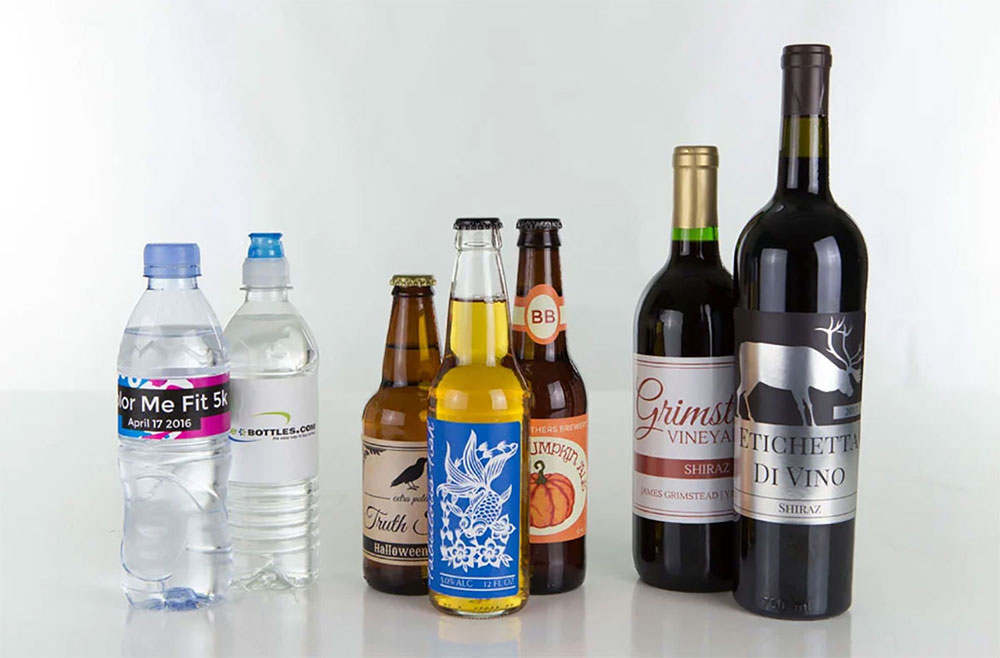
Die Auswahl der besten Schriftarten für Etiketten ist wie das Aussuchen des perfekten Outfits für ein großes Ereignis. Es kann alles verändern.
Stellen Sie sich vor, Sie betreten einen Laden, Ihre Blicke schweifen über die Regale, und da ist es – ein Produkt, das heraussticht, nicht nur wegen seines Inhalts, sondern wegen seiner Präsentation. Das ist die Macht der Schriftarten.
In diesem Tauchgang in die Welt der Typografie enthüllen wir die geheime Zutat, die Etiketten nicht nur lesbar, sondern unvergesslich macht.
Ob Sie ein Kleinunternehmer sind, der seine Produktverpackung aufpeppt, oder eine neugierige Seele, die vom Einfluss der Typografie im Marketing fasziniert ist, dies ist für Sie.
Wir sprechen über alles, von Serifen- und serifenlosen Schriftarten, die Professionalität ausstrahlen, bis hin zu ausgefallenen handschriftlichen Schriftarten, die diesen handwerklichen Vibe vermitteln.
Am Ende dieser Reise werden Sie mit Wissen über Schriftlesbarkeit, Designprinzipien und darüber ausgestattet sein, wie Schriftarten mit Ihrer Markenidentität übereinstimmen können.
Machen Sie sich bereit, eine Vielzahl von Typografietrends zu erkunden und wie sie Ihr Etikettenspiel verbessern können. Von gut lesbaren Schriftarten für die kleinen Etiketten bis hin zu fetten Schriftarten für einen auffälligen Look, wir haben alles abgedeckt.
Die besten Schriftarten für Etiketten
| Schriftartenname | Kategorie/Stil | Lesbarkeit | Verwendungszweck | Besondere Merkmale |
|---|---|---|---|---|
| Garamond | Serif | Hoch | Fließtext, anspruchsvolle Etiketten | Elegant, klassisches Design, gut für den Druck |
| Butler | Serif | Hoch | Stilvolle Etiketten, Überschriften | Moderne Interpretation der traditionellen Serifenschrift |
| Yeseva One | Serif | Mittel | Dekorative Etiketten, Schlagzeilen | Einzigartig, fett mit hohem Kontrast |
| Didot | Serif | Mittel | Etiketten für hochwertige Produkte, Mode | Stilvoll, gehoben mit dünnen Serifen |
| Times New Roman | Serif | Hoch | Allgemeine Nutzung, Fließtext | Klassisch, bekannt, weit verbreitet |
| Cambria | Serif | Hoch | Allgemeine Etiketten, gut lesbarer Druck | Optimierte Lesbarkeit auf Bildschirmen |
| Georgia | Serif | Hoch | Vielseitige Etiketten, Bildschirm und Druck | Hervorragende Lesbarkeit, elegant |
| Baskerville | Serif | Hoch | Traditionelle Etiketten, Buchtext | Gepflegtes, professionelles Design |
Arten von Schriftarten für Etiketten
Serifenschriftarten
Ah, Serifenschriftarten, die klassische Wahl! Denken Sie an sie wie an das zeitlose kleine Schwarze in Ihrem Kleiderschrank. Es sind nicht nur Schriftarten; sie sind eine Aussage von Eleganz und Vertrauenswürdigkeit. Warum? Weil diese Schriftarten jene kleinen Füße am Ende jedes Buchstabens haben, bekannt in der Designwelt als Serifen. Und raten Sie mal? Sie machen Ihre Etiketten super lesbar, besonders für längeren Text.
Einige Top-Picks? Garamond – er ist wie jener weise, alte Professor, der weiß, wie man komplizierte Dinge einfach aussehen lässt. Dann gibt es Butler – stellen Sie sich einen Butler vor, aber für Ihre Worte, der sie scharf und anspruchsvoll aussehen lässt. Yeseva One fügt eine Note von Wärme hinzu, ideal für jene gemütlichen, wohlfühlenden Produkte.
Didot ist Ihre Wahl für Luxusvibes auf hohem Niveau. Es ist, als würden Sie Ihrem Text einen Designanzug anziehen. Und wer könnte Times New Roman und Cambria vergessen? Sie sind wie Ihre zuverlässigen Freunde, die nie im Stich lassen, perfekt für jedes Etikett, das Zuverlässigkeit und Komfort kommunizieren möchte. Georgia und Baskerville fügen einen Hauch von altmodischem Charme hinzu, wodurch Ihre Etiketten sich anfühlen wie ein klassischer Roman.
Serifenlose Schriftarten
Wechseln wir die Gänge und sprechen über serifenlose Schriftarten. Serifenlos bedeutet „ohne Serifen“, und diese Schriftarten stehen für moderne, klare Linien. Sie sind wie das trendige, minimalistische Outfit, das Sie tragen, das modernen Schick ausstrahlt.
Erstens Aileron, schlicht und vielseitig. Es ist wie die Jeans, die zu allem passt. Maison Neue? Sie ist die anspruchsvolle Cousine, die einen Hauch von Eleganz mitbringt. Und Sofia – oh, sie ist spaßig und freundlich, perfekt für Etiketten, die zugänglich wirken wollen.
Omnes ist Ihre unbeschwerte Schriftart, während Helvetica und Arial die universellen Freunde in der Schriftartenwelt sind, bekannt und von allen geliebt. Für ein futuristisches Gefühl gibt es Futura – denken Sie daran als Ihre Sci-Fi-Fantasie in Schriftform. Calibri und Verdana sind Allrounder, großartig für nahezu jedes Etikett, während Roboto einen mechanischen und doch menschlichen Touch in den Mix bringt.
Schreibschriftarten
Okay, lassen Sie uns in die Welt der Schreibschriftarten eintauchen. Diese Schriftarten sind wie die Handschrift, die Sie sich wünschen, voller Flair und Persönlichkeit. Perfekt, wenn Sie möchten, dass Ihre Etiketten persönlich und handgefertigt wirken. Lucia Script? Es ist wie ein schön geschriebener Brief. Elegant, doch zugänglich. Satisfy? Genau wie sein Name hinterlässt es einen süßen, zufriedenstellenden Eindruck, ideal für Lebensmitteletiketten oder alles, was einen Hauch von Verspieltheit vermitteln möchte.
Jetzt, Bella Donna – diese hat eine ausgefallene Ausstrahlung, wie Kalligrafie, die Sie auf einer Hochzeitseinladung sehen würden. Homemade Apple bringt ein rustikales, heimeliges Gefühl auf den Tisch und erinnert an Omas Apfelkuchen. Und Loved by the King hat eine königliche Note, mit Schleifen und Wirbeln, die für eine Königin geeignet sind. Sue Ellen Francisco rundet es mit einem lässigen, luftigen Stil ab, wie eine schnelle Notiz, die von einem Freund gekritzelt wurde.
Display- und Dekorative Schriftarten
Weiter geht’s mit Display- und dekorativen Schriftarten – das sind die Hingucker. Sie sind wie das auffällige Schmuckstück, das Blicke auf sich zieht. Lemonade ist frisch und spaßig, perfekt für ein sommerliches Vibe. Shortcut Vintage Bundle Font nimmt Sie mit zurück in die Zeit mit seinem Retro-Charme, großartig für Marken, die eine nostalgische Note wollen.
Mermaid Typeface taucht tief in die Fantasie ein und gibt ein mystisches Gefühl unter Wasser. Gunnar ist stark und fett, und macht auf jedem Etikett eine Aussage. Buchin ist schrullig und unerwartet, für Marken, die es wagen, anders zu sein. Whimsy, wie der Name schon sagt, fügt eine verspielte, humorvolle Note hinzu.
Und dann gibt es Watch und Asthenia. Watch ist wie diese schlanke, moderne Uhr, die Sie tragen – es dreht sich alles um ein klares, wirkungsvolles Design. Asthenia, mit seinen dünnen, zarten Linien, ist perfekt für hochwertige, anspruchsvolle Produkte.
Handschriftliche und Pinselschriftarten
Zuletzt handschriftliche und Pinselschriftarten. Diese Schriftarten sind wie eine persönliche Signatur, jede mit ihrem eigenen Charakter und Stil. Habisa ist entspannt und unprätentiös, großartig für lässige oder handwerkliche Produkte. Crafty Girls bringt einen kreativen, künstlerischen Vibe, ideal für Bastelbedarf oder spaßige, jugendliche Marken.
Shadows into the Light und Waiting for the Sunrise sind leicht, luftig und optimistisch, perfekt für inspirierende oder Wellness-Produkte. Und Carbonera, mit seinen fett gedruckten Pinselstrichen, macht eine starke, selbstbewusste Aussage, großartig für Marken, die auffallen wollen.
Kriterien für Schriftlesbarkeit und -leserlichkeit
Wenn es darum geht, die besten Schriftarten für Etiketten auszuwählen, geht es nicht nur darum, hübsch auszusehen. Wir müssen darüber nachdenken, wie einfach es ist, diese Schriftarten zu lesen, besonders wenn jemand in Eile im Laden ist, wissen Sie?
Lesbarkeitsfaktoren
Erstens: Lesbarkeit. Es ist wie das Einrichten der richtigen Stimmungsbeleuchtung für ein Date. Wir sprechen über den Kontrast und die Sichtbarkeit der Schrift gegenüber dem Hintergrund des Etiketts. Zu viel oder zu wenig Kontrast, und Sie haben Ihr Publikum verloren.
Dann gibt es den Abstand zwischen den Buchstaben. Haben Sie schon einmal versucht, etwas zu lesen, bei dem die Buchstaben zusammengequetscht sind? Nicht lustig, oder? Der richtige Abstand, auch Kerning genannt, macht einen großen Unterschied.
Schließlich hat jede Schriftart ihren eigenen Stil, aber wir benötigen deutliche Buchstabenformen. Sie wollen nicht, dass das ‚b‘ wie ein ‚d‘ aussieht und allerlei Verwirrung stiftet.
Dyslexie-freundliche Schriftarten
Jetzt sprechen wir über etwas sehr Wichtiges: dyslexie-freundliche Schriftarten. Es geht um Inklusion. Diese Schriftarten sind so konzipiert, dass sie einfacher zu lesen sind, besonders für Menschen mit Dyslexie. Sie haben in der Regel schwerere untere Teile, um zu verhindern, dass die Buchstaben im Kopf des Lesers kippen. Das ist durchdachtes Design, oder?
Kreative und ausdrucksstarke Schriftwahl
Okay, jetzt machen wir es ein wenig interessanter mit einigen kreativen Schriftwahlen. Hier können wir unseren Stil und unsere Persönlichkeit zur Schau stellen.
Handgemachte und fantasievolle Schriftarten
Handgemachte und fantasievolle Schriftarten sind wie ein Farbtupfer auf einer Leinwand. Sie brechen die Normen und fügen eine persönliche Note hinzu. Whimsy und Lemonade sind perfekte Beispiele. Sie sind wie jener schrullige Freund, der immer Spaß macht – sie bringen Leben und Energie in Ihr Etikett.
Retro- und Vintage-Stile
Lust auf Nostalgie? Retro- und Vintage-Stile wie Mermaid Typeface nehmen Sie mit zurück in die Zeit. Sie sind wie diese coolen, altmodischen Platten, die Ihre Eltern gespielt haben. Perfekt für Marken, die eine nostalgische und zeitlose Ausstrahlung hervorrufen wollen.
Moderne und fette Schriftarten
Und für diejenigen, die eine Aussage treffen wollen, sind moderne und fette Schriftarten der richtige Weg. Gunnar und Buchin flüstern nicht nur; sie rufen. Sie sind wie jenes auffällige Kunstwerk, das Ihnen ins Auge fällt und Sie zum Staunen bringt.
Kombination von Schriftarten für effektives Etikettendesign
Jetzt mischen wir ein wenig! Die Wahl der besten Schriftarten für Etiketten geht nicht nur darum, eine auszuwählen und fertig. Manchmal geht es darum, wie Sie sie kombinieren. Wie Erdnussbutter und Gelee, manche Schriftarten funktionieren einfach besser zusammen.
Kombination verschiedener Schriftstile
Stellen Sie sich vor, Sie mischen eine Schreibschrift mit einer serifenlosen Schrift. Die Schreibschrift bringt das Flair, und die serifenlose hält alles geerdet. Es ist wie ein Gespräch zwischen zwei verschiedenen Charakteren auf Ihrem Etikett. Die eine ist das Leben der Party (Schreibschrift) und die andere ist der coole, gesammelte Typ (Serifenlos).
Zum Beispiel, die Kombination von etwas Ausgefallenem wie Bella Donna mit einem geradlinigen Arial kann auf Ihrem Etikett ein Gleichgewicht schaffen, das sowohl auffällig als auch leicht zu lesen ist.
Schrift-Hierarchie und Informationslayout
Jetzt sprechen wir über Hierarchie. Es geht nicht nur darum, was Sie sagen; es geht darum, wie Sie es präsentieren. Die Schlüsselinformationen, wie Ihr Markenname oder das Hauptmerkmal Ihres Produkts, sollten hervorstechen. Verwenden Sie dafür eine Schriftart, die auffällt – vielleicht etwas Fettes oder mit ein bisschen Persönlichkeit.
Die restlichen Informationen? Da kommt Ihre sekundäre Schriftart zum Einsatz. Diese sollte zurückhaltender sein, wie ein Calibri oder Helvetica, damit sie nicht die Hauptrolle stiehlt, aber das Teamwork dennoch funktioniert.
Praktische Tipps und bewährte Verfahren
Okay, Sie haben Ihre Schriftarten, Sie haben sie kombiniert, aber es gibt noch ein paar Dinge zu beachten, um die besten Schriftarten für Etiketten zu meistern.
Verständnis Ihrer Marke und Ihres Publikums
Ihre Schriftwahl sollte mit dem Wesen Ihrer Marke harmonieren. Wenn Sie ganz modern und technisch sind, ist eine schlanke, saubere Schrift Ihr Freund. Verkaufen Sie hausgemachte, biologische Marmeladen? Vielleicht etwas Handschriftliches oder Rustikales.
Denken Sie auch darüber nach, wer Ihre Zielgruppe ist. Schriftarten, die bei einem jüngeren Publikum ankommen, funktionieren möglicherweise nicht gleich gut bei einer reiferen Zielgruppe. Es geht darum, ihre Sprache zu sprechen.
Experimentieren und Testen
Haben Sie keine Angst zu experimentieren. Mischen und kombinieren Sie, probieren Sie verschiedene Kombinationen aus. Manchmal schaffen die unerwartetsten Paarungen die denkwürdigsten Etiketten.
Und testen Sie sie! Was auf Ihrem Bildschirm gut aussieht, sieht möglicherweise nicht genauso gut gedruckt auf einem Etikett aus. Überprüfen Sie die Lesbarkeit, Sichtbarkeit und den allgemeinen Appeal. Vielleicht auch ein Feedback von Freunden oder potenziellen Kunden einholen. Schließlich sind sie diejenigen, die Sie beeindrucken wollen.
FAQs zu den besten Schriften für Etiketten
Was macht eine Schriftart für Etiketten geeignet?
Die richtige Schriftart für Etiketten auswählen? Es geht alles um Lesbarkeit und die Anpassung an die Ausstrahlung Ihrer Marke.
Sie wollen etwas, das aus der Ferne leicht zu lesen, zur Persönlichkeit des Produkts passt und sich im Regal abhebt. Denken Sie an Typografietrends und Markenidentität bei Ihrer Auswahl.
Wie entscheide ich mich zwischen Serifen- und Serifenlosen Schriftarten für Etiketten?
Serifenschriftarten vermitteln ein klassisches, vertrauenswürdiges Gefühl. Großartig für traditionelle Produkte. Serifenlos? Sie sind sauber, modern, perfekt für ein zeitgenössisches Aussehen.
Ihre Wahl sollte den Charakter Ihres Produkts widerspiegeln. Denken Sie an Lesbarkeit und wie die Schriftart mit Ihren Designprinzipien übereinstimmt.
Sind Schreibschriftarten eine gute Wahl für Etiketten?
Absolut, wenn Sie eine persönliche, handwerkliche Ausstrahlung anstreben. Schreibschriftarten, wie Lucia Script oder Satisfy, fügen eine Note von Eleganz und Einzigartigkeit hinzu.
Achten Sie nur darauf, dass sie lesbar bleiben, insbesondere für wichtige Informationen wie Zutaten oder Anweisungen.
Welche Rolle spielen Schriftgröße und -farbe im Etikettendesign?
Riesig! Die Schriftgröße gewährleistet die Lesbarkeit; zu klein, und es ist anstrengend, zu groß, und es wirkt überwältigend. Farbkontrast ist entscheidend für die Sichtbarkeit.
Stellen Sie sicher, dass Ihre Schriftfarbe sich vom Hintergrund abhebt, aber immer noch mit Ihrer gesamten Markenidentität übereinstimmt.
Kann ich mehrere Schriftarten auf einem einzigen Etikett verwenden?
Ja, aber halten Sie es ausgewogen. Kombinieren Sie eine fette Schrift für die Überschrift mit einer einfacheren für die Details.
Dies schafft eine Schrifthierarchie, lenkt das Auge des Betrachters und hebt wichtige Informationen hervor. Denken Sie daran, weniger ist mehr. Zu viele Schriftarten können unübersichtlich wirken.
Welche Fehler sollte man beim Auswählen von Schriften für Etiketten vermeiden?
Überkomplizieren ist ein großer Fehler. Zu viele Stilarten, Größen oder Farben können überwältigend sein. Die Lesbarkeit nicht zu berücksichtigen, insbesondere bei kleinen Etiketten, ist ein weiterer Fehler.
Auch das Übersehen, wie die Schriftart die Persönlichkeit Ihrer Marke widerspiegelt, kann zu einer Diskrepanz mit Ihrem Publikum führen.
Welche Rolle spielen Schrifttrends im Etikettendesign?
Schrifttrends können Ihr Etikett aktuell und frisch erscheinen lassen. Aber es ist ein feiner Balanceakt.
Sie wollen relevant bleiben, ohne Ihre Markenidentität zu verlieren oder in ein paar Jahren ein veraltetes Aussehen zu haben. Behalten Sie Typografietrends im Auge, aber bleiben Sie Ihrer Marke treu.
Ist es wichtig, das Produkt zu berücksichtigen, wenn man eine Schriftart wählt?
Unbedingt. Die Schriftart sollte zur Persönlichkeit des Produkts passen. Ein technisches Produkt benötigt möglicherweise eine schlanke, moderne Schriftart, während ein organisches Snackprodukt besser zu einem rustikaleren, natürlichen Stil passt. Es geht darum, die Schriftart das Produkt ergänzen zu lassen.
Wie kann ich die Wirksamkeit der Schriftwahl meines Etiketts testen?
Machen Sie eine Nachbildung und drucken Sie sie aus. Sehen Sie, wie sie in echter Größe und unter verschiedenen Lichtverhältnissen aussieht.
Sie können auch Feedback von anderen einholen, insbesondere von Ihrer Zielgruppe. Manchmal sieht das, was auf dem Bildschirm gut aussieht, im Druck nicht so gut aus.
Fazit
So, wir haben uns also durch die Welt der besten Schriften für Etiketten durchgearbeitet, nicht wahr? Von der zeitlosen Eleganz der Serifenschriften bis zu den klaren Linien der serifenlosen Schriften, jede Schriftart hat ihre eigene Geschichte zu erzählen.
Denken Sie daran, Lesbarkeit und Markenidentität sind der Schlüssel. Ihr Etikett ist nicht nur ein Aufkleber auf einem Produkt; es ist eine geschichtenerzählende Leinwand. Ob es der warme, persönliche Touch von Schreibschriftarten oder die kühne Aussage von Display-Schriftarten ist, jede Wahl malt einen Teil des Bildes Ihrer Marke.
Typografie ist nicht nur eine Frage des guten Aussehens. Es geht darum, eine Verbindung herzustellen, zu Ihrem Publikum zu sprechen, ohne ein Wort zu sagen. Es geht um Branding, Marketing und darum, sich in einem überfüllten Regal abzuheben.
Also nehmen Sie diese Einsichten, experimentieren Sie und finden Sie die perfekte Schriftart, die die Sprache Ihrer Marke spricht. Denn letztendlich kann die richtige Schriftart ein einfaches Etikett in einen unvergesslichen Teil des Kundenerlebnisses verwandeln. Lassen Sie Ihre Etiketten mehr als nur informieren; lassen Sie sie inspirieren.